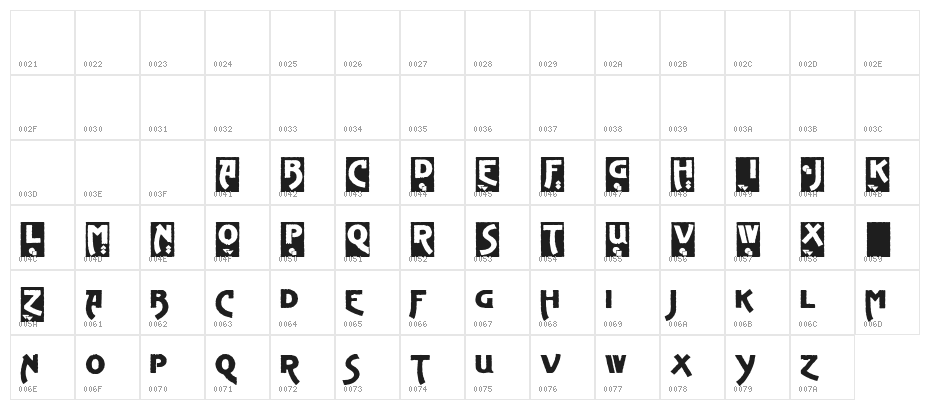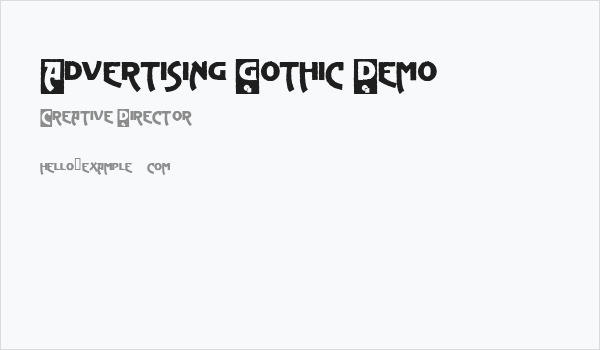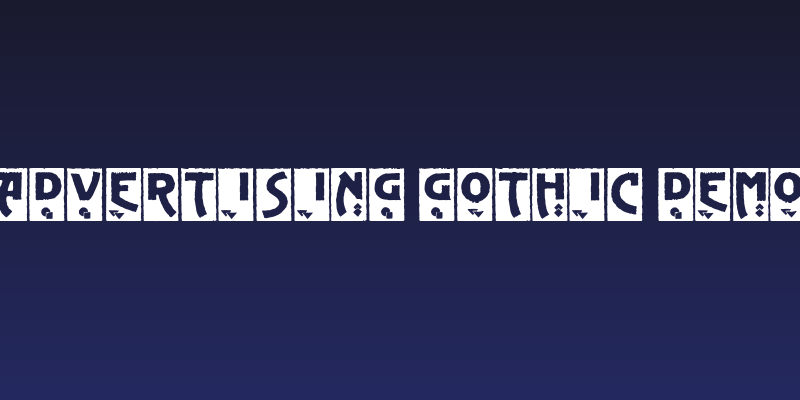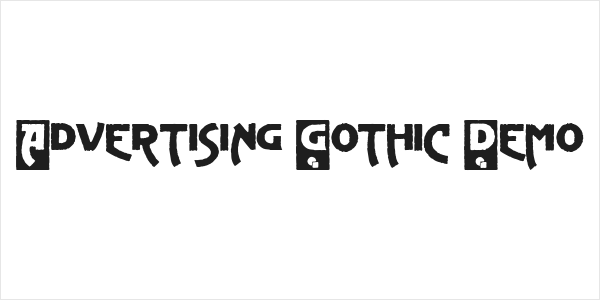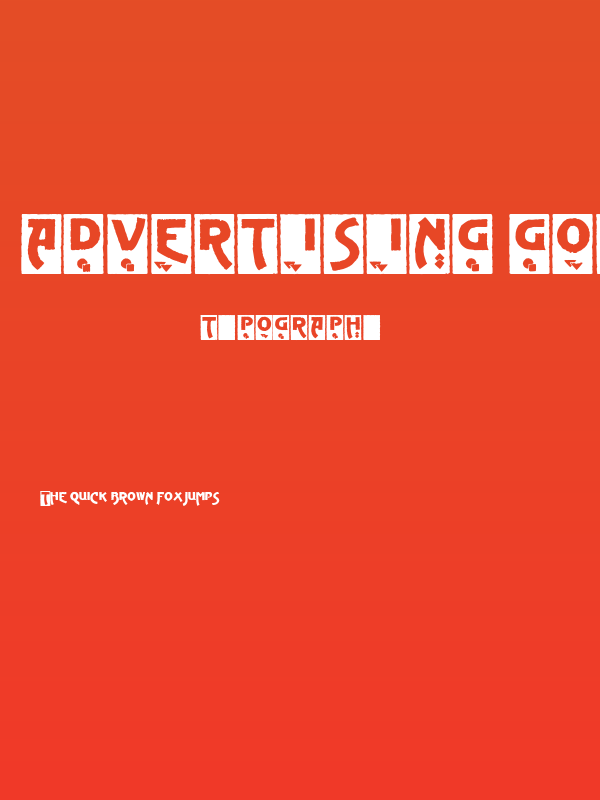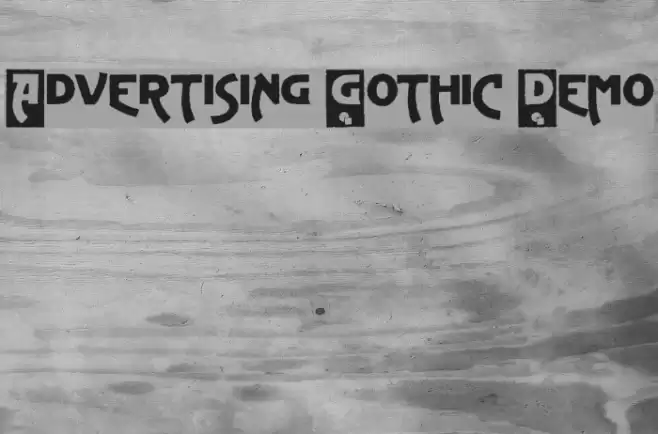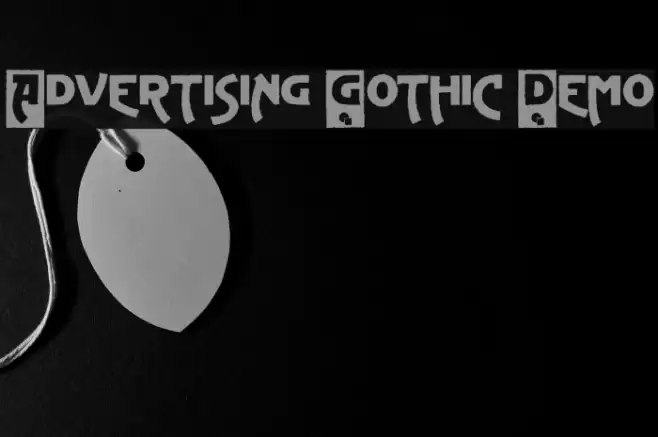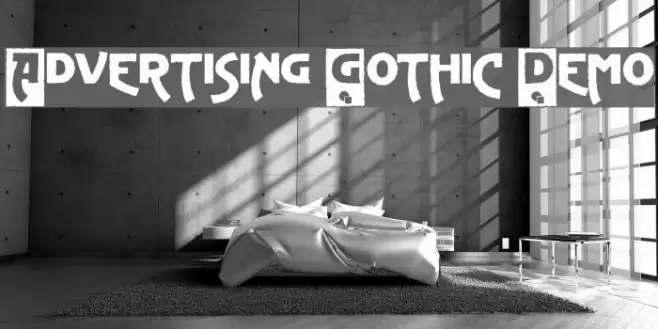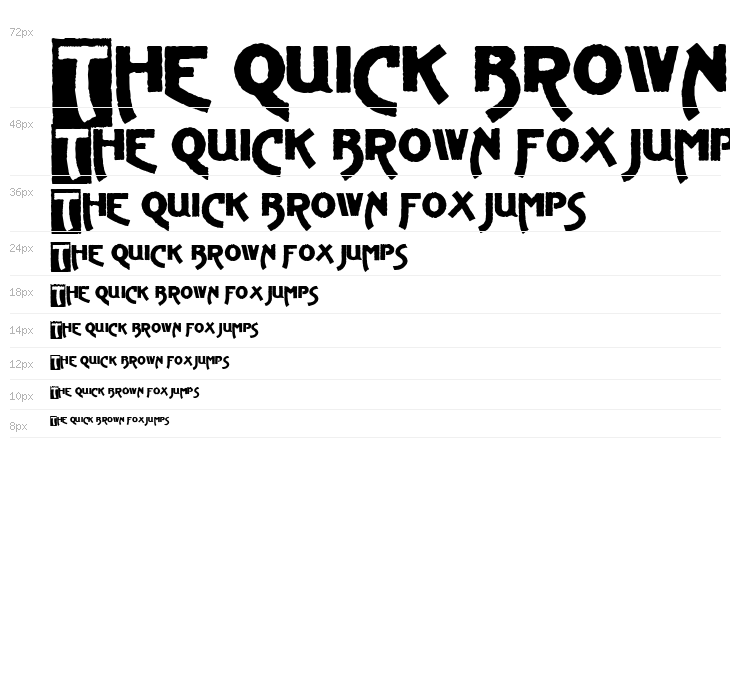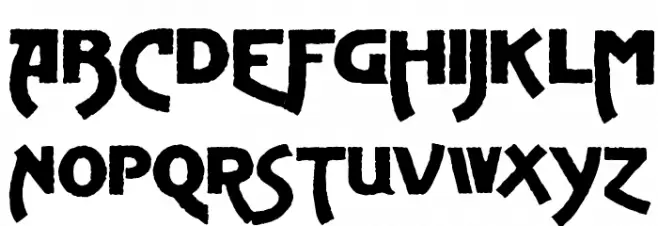
Advertising Gothic Demo Font
| Vorgeschlagene Projekte | Ideal for use in posters, book covers, branding, and any project requiring a dramatic, historical aesthetic. |